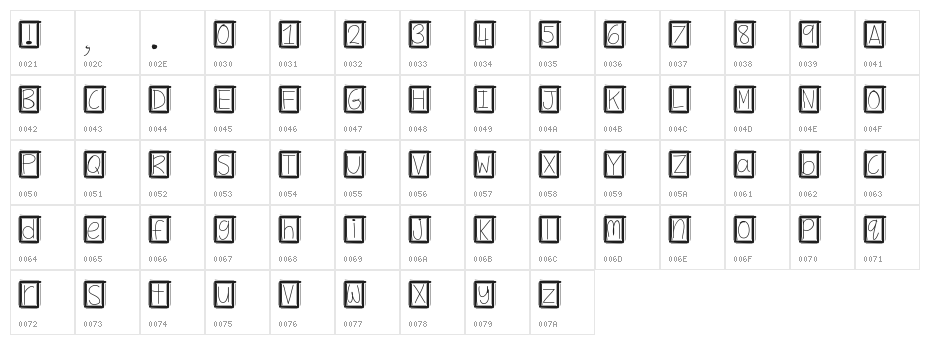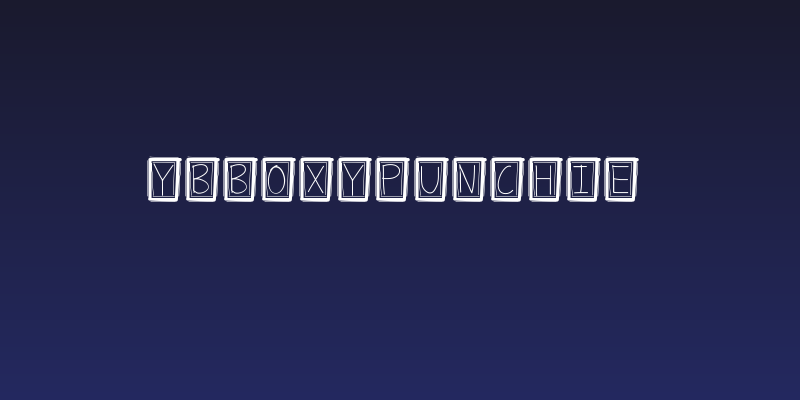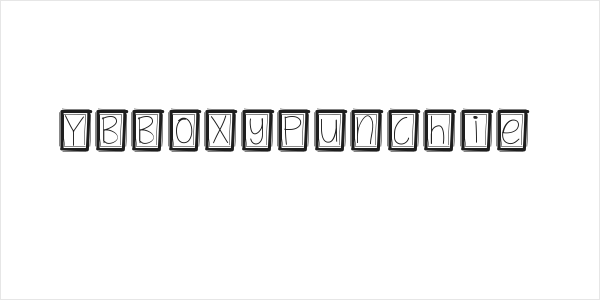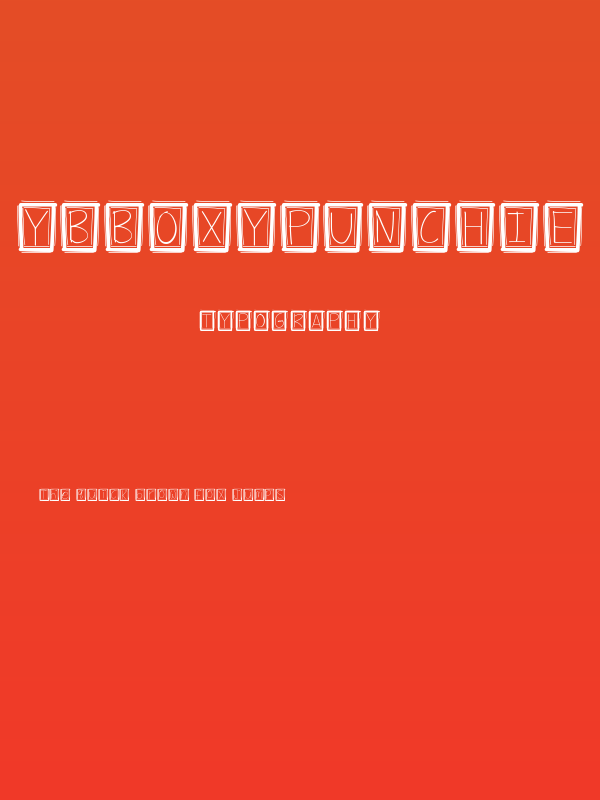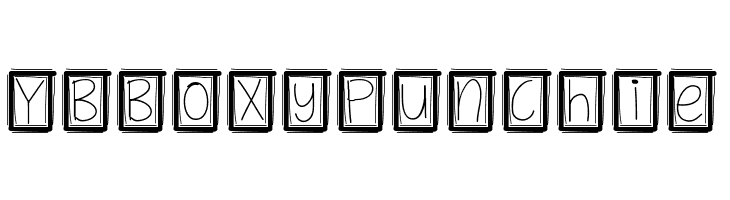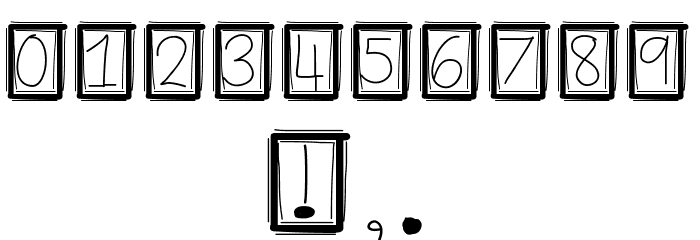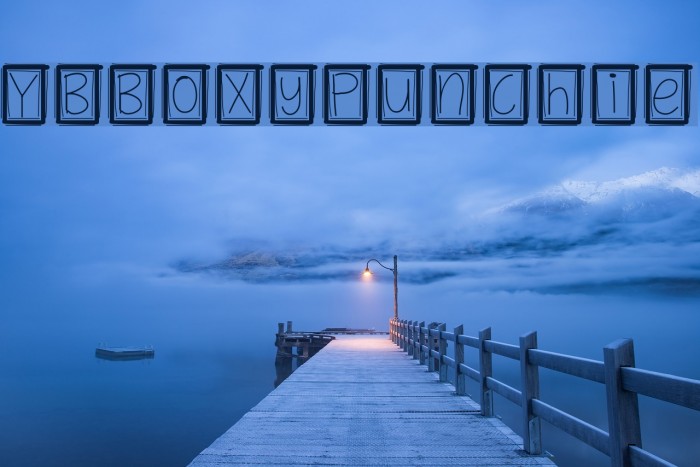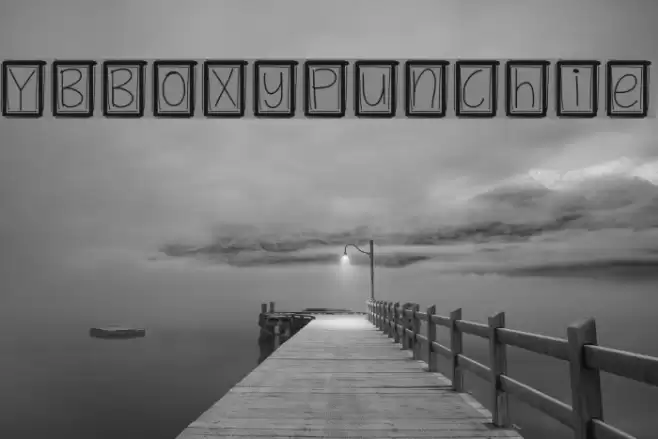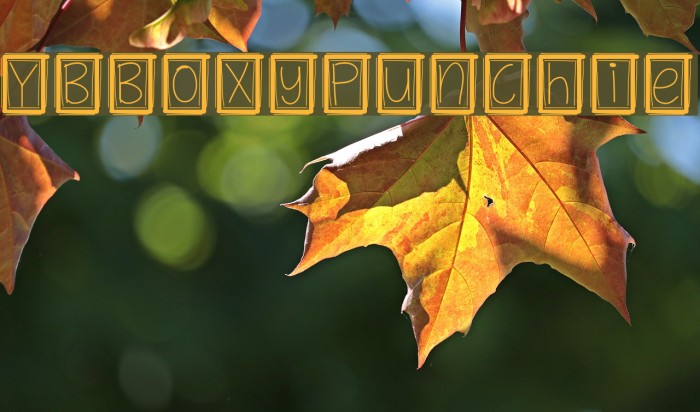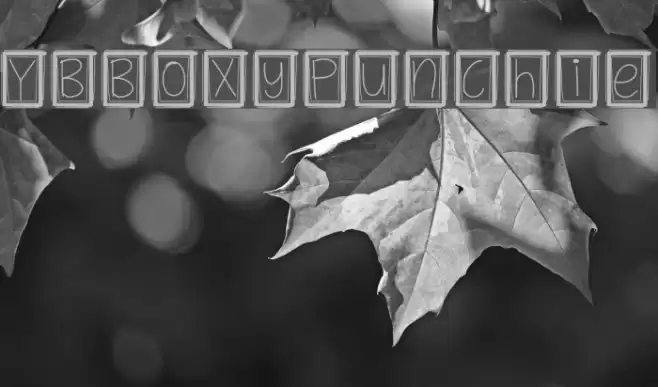
YBBoxyPunchie Font
Diese Schriftart enthält 69 Zeichen. Klicken Sie auf ein Zeichen für Details.
| Vorgeschlagene Projekte | Ideal for children's books, playful branding, posters, and creative invitations. |